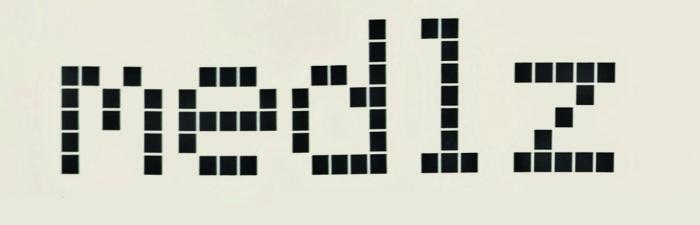
Ich mach's kurz: auf der Webseite www.medlz.de wird als Logo und in den Menüs ein Pixelfont verwendet. Es liegt mir auf der Zunge, aber ich komme nicht auf den Namen des Fonts. Oakland oder Universal von Emigre ist es nicht. Die Pixel sind auseinander und das d ist "eingebuchtet". Kann mir jemand schnell mal den Klaps auf den Hinterkopf geben? :hammer: